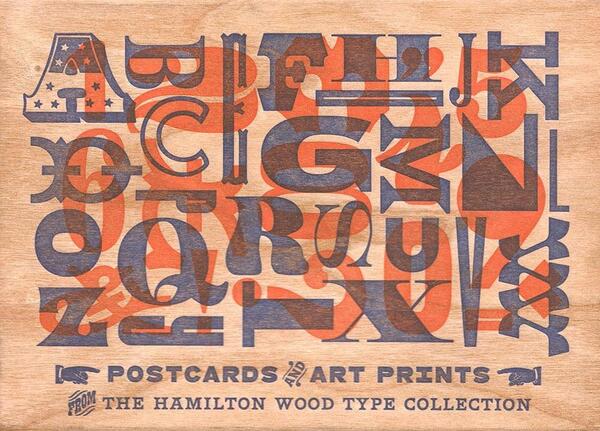
Postkartenset: Hamilton Wood Type Collection
Die Holzbuchstabenfabrik von J. Edward Hamilton wurde 1880 gegründet und wuchs rasch zum größten Holzbuchstabenhersteller der USA heran. Das historische Erbe der Fabrik wird heute von der Two Rivers Historical Society in einem eigenen Museum bewahrt. Das Hamilton Wood Type and Printing Museum besteht seit dem Jahr 2000. In Zusammenarbeit mit Chronicle Books hat das Museum eine wertige Postkartenserie veröffentlicht.
In einem Kartonschuber in Holzoptik befindet sich eine kupferfarben bedruckte, schwarze Klappbox. Darin finden sich:
• 6 mehrfarbig gedruckte Original-Buchdruckpostkarten aus dem Museum.
• 24 Offset-Postkarten mit Fotos aus dem Museum. Die Fotos zeigen insbesondere Detailaufnahmen der Holzdrucklettern. Auf der Rückseite gibt es jeweils einen kurzen Text mit Erklärungen zum Bildinhalt.
• Ein gefaltetes Poster, das auf einer Seite die für Holzbuchstaben relevanten Schriftstile vorstellt und auf den Textseiten der Rückseite Details zur Fabrik, zum Museum und zum Buchdruck erklärt.